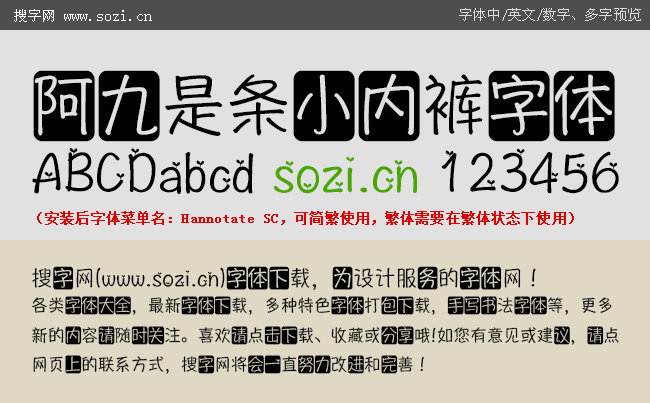
阿九是條小內(nèi)褲字體
搜字網(wǎng)給大家提供一款很有趣的手機中文字體下載。修改者給這款字體叫阿九是條小內(nèi)褲字體,光看名字就很有趣吧,這款手機中文字體中一些字做了黑底反白效果,該中文字體簡潔明快,卡通味實足,趣味性強,又保持了文字的識別度,適合喜歡簡單而又想有點小個性的朋友在手機上安裝使用。